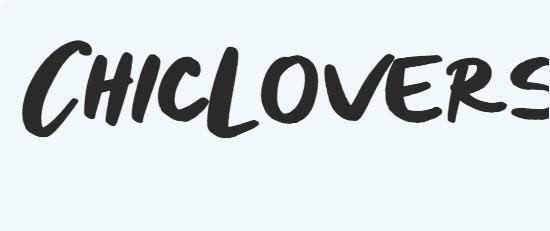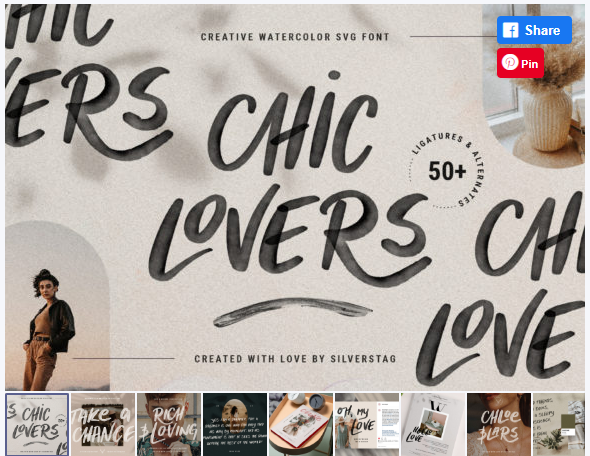
Chic Lovers - это стильный дисплейный шрифт с начесом, отличающийся идеальной модностью. Независимо от того, используете ли вы его для создания предметов, цифрового дизайна, презентаций или изготовления поздравительных открыток, он идеален!